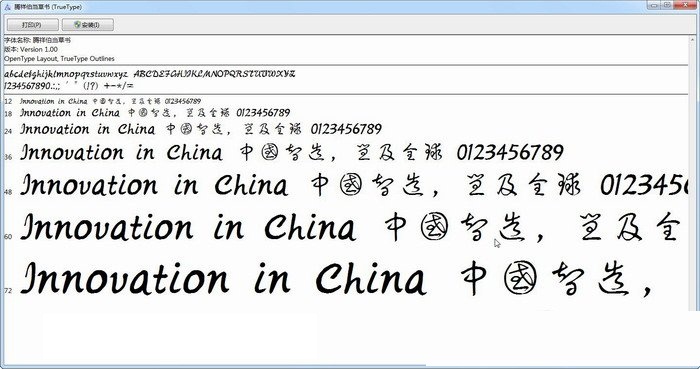
騰祥伯當(dāng)草書(shū)字體是一款專(zhuān)門(mén)為用戶(hù)用于書(shū)法設(shè)計(jì)的字體,獨(dú)特的字體風(fēng)格給你不一樣的體驗(yàn),有需要者歡迎下載!
騰祥伯當(dāng)草書(shū)字體以草書(shū)為原型,運(yùn)筆飄忽快捷,筆跡廋勁,至廋而不失其肉,形體端秀而骨架勁挺,是種風(fēng)格相當(dāng)獨(dú)特的字體。